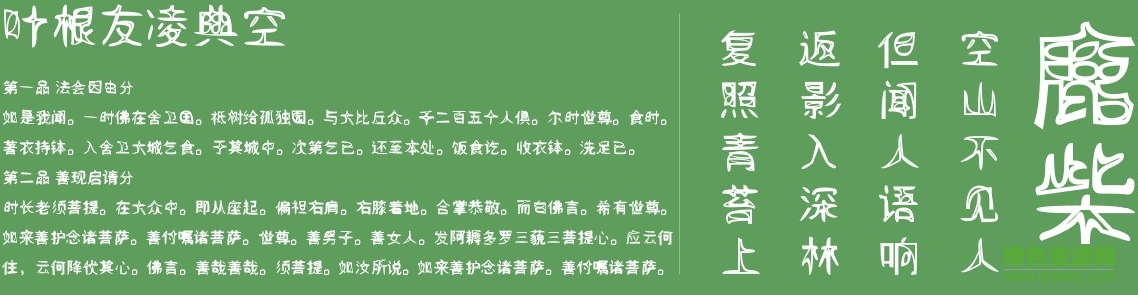
葉根友凌典空
葉根友凌典空字體是由中國(guó)書(shū)法奇人,五筆同書(shū)世界首創(chuàng)者,連筆空心字吉尼斯世界紀(jì)錄保持者葉根友先生親自書(shū)寫(xiě)的一款字體,是葉根友先生平時(shí)書(shū)寫(xiě)最多的一種,也是最為實(shí)用的風(fēng)格。字體大方,流暢。歡迎下載!
葉根友凌典空字體